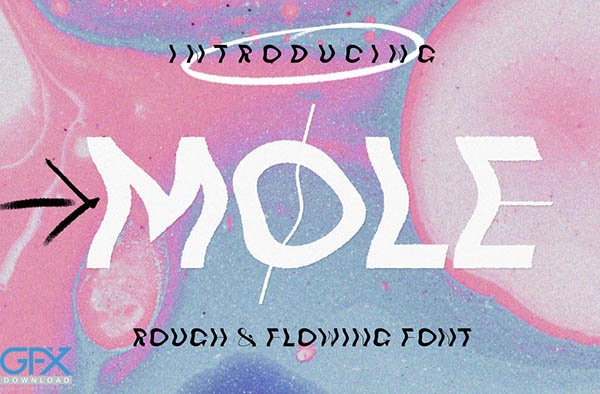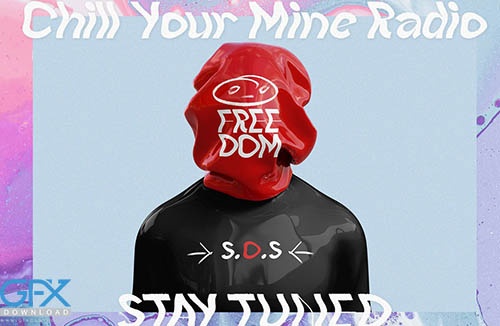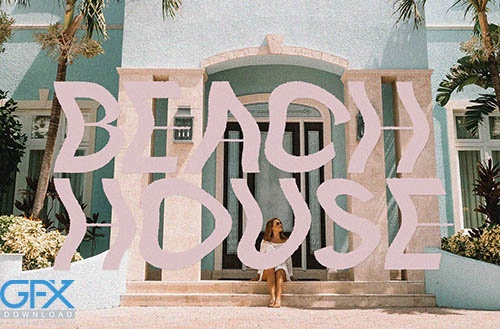
فونت تزئینی MOLE
دانلود رایگان فونت تزئینی MOLE یک فونت نمایشی تزئینی است. MOLE با سبک ROUGH & FLOWING عرضه می شود، باعث می شود که این حروف در تمام پروژه های طراحی مورد استفاده قرار گیرد و برای جفت شدن با حروف اسکریپت یا فونت های دست ساز، سرفصل ها، پوسترها، بسته بندی ها، کارت پستال ها، دعوت نامه ها، تابلوهای عروسی، تابلوهای نقاشی، تابلوها، و موارد بیشتر ایده آل است.